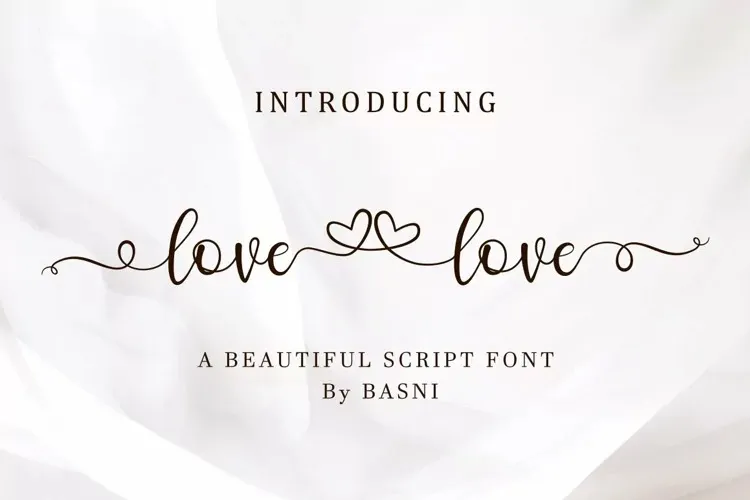
Lovelove Font – Download Grátis
A fonte Lovelove é uma elegante tipografia feita para designers modernos. Com seu estilo manuscrito fino, apresenta uma aparência luxuosa e sofisticada que certamente vai dar um toque atraente às suas criações. Perfeita tanto para o branding quanto para criar logotipos, marca d’água, cartões de visita, roupas, revistas ou qualquer outro projeto gráfico, a Lovelove consegue capturar a atenção do olhar e oferece um toque natural sem igual. Esta fonte perfeita combina com diversos formatos de mídia, desde materiais impressos até projetos web, tornando-a uma opção versátil para qualquer designer em busca de dar seu design aquela finalização única e desejada. A Lovelove não deixará sua marca como a última impressão!